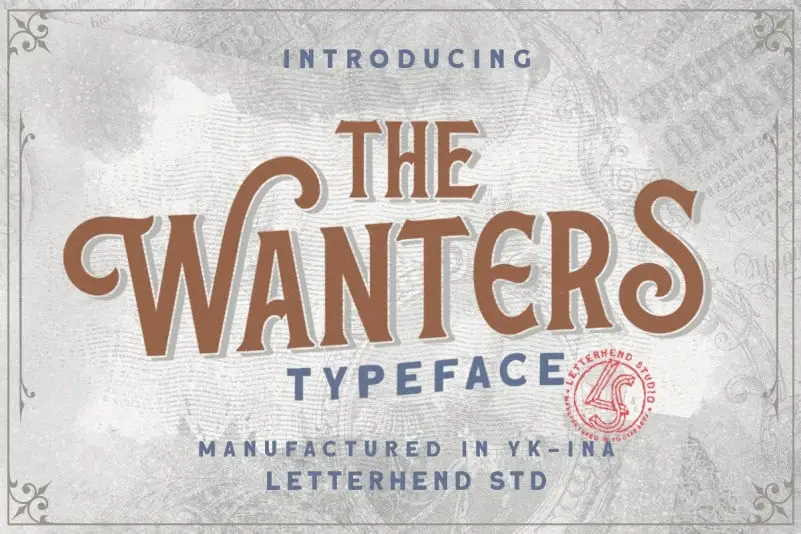
The Wanters Display Font – Download Grátis
A fonte The Wanters Display é uma elegante tipografia com serifas curvadas equirúpicas. Perfeita para aplicação em branding, headlines ou qualquer formato que seja requintado mas simples. Ela foi criada pelo Letterhend Studio e tem um toque nostálgico sem perder seu luxo moderno. Esta fonte apresenta formas únicas e forte personalidade através de ornamentos e swashes. É perfeita para criação de logotipos, além de diversos formatos formais como cartas de convite, embalagens, revistas, livros de casamento, embalagens, moda, maquiagem, estação e qualquer propósito de anúncio. Um charme para o seu próximo projeto visual.